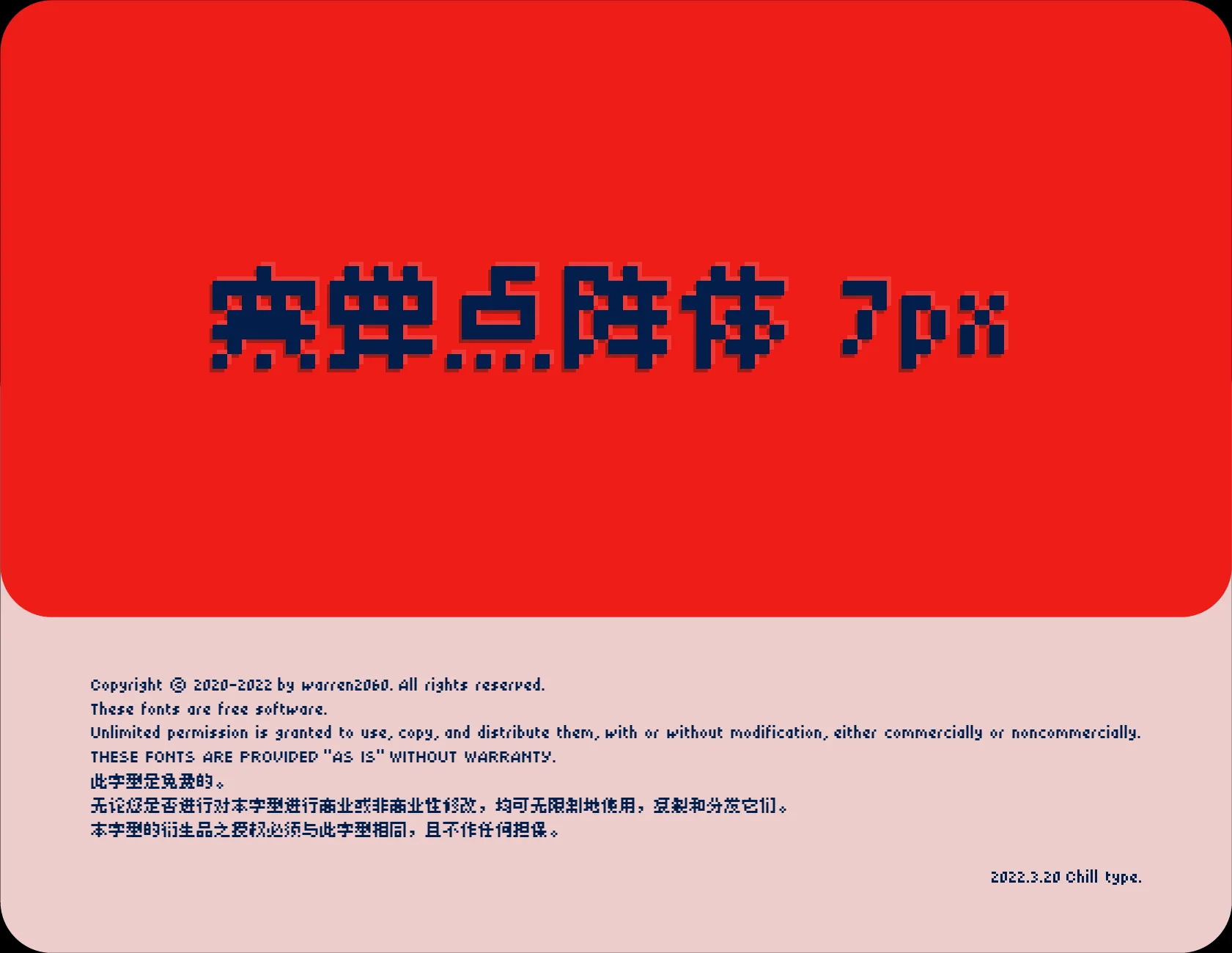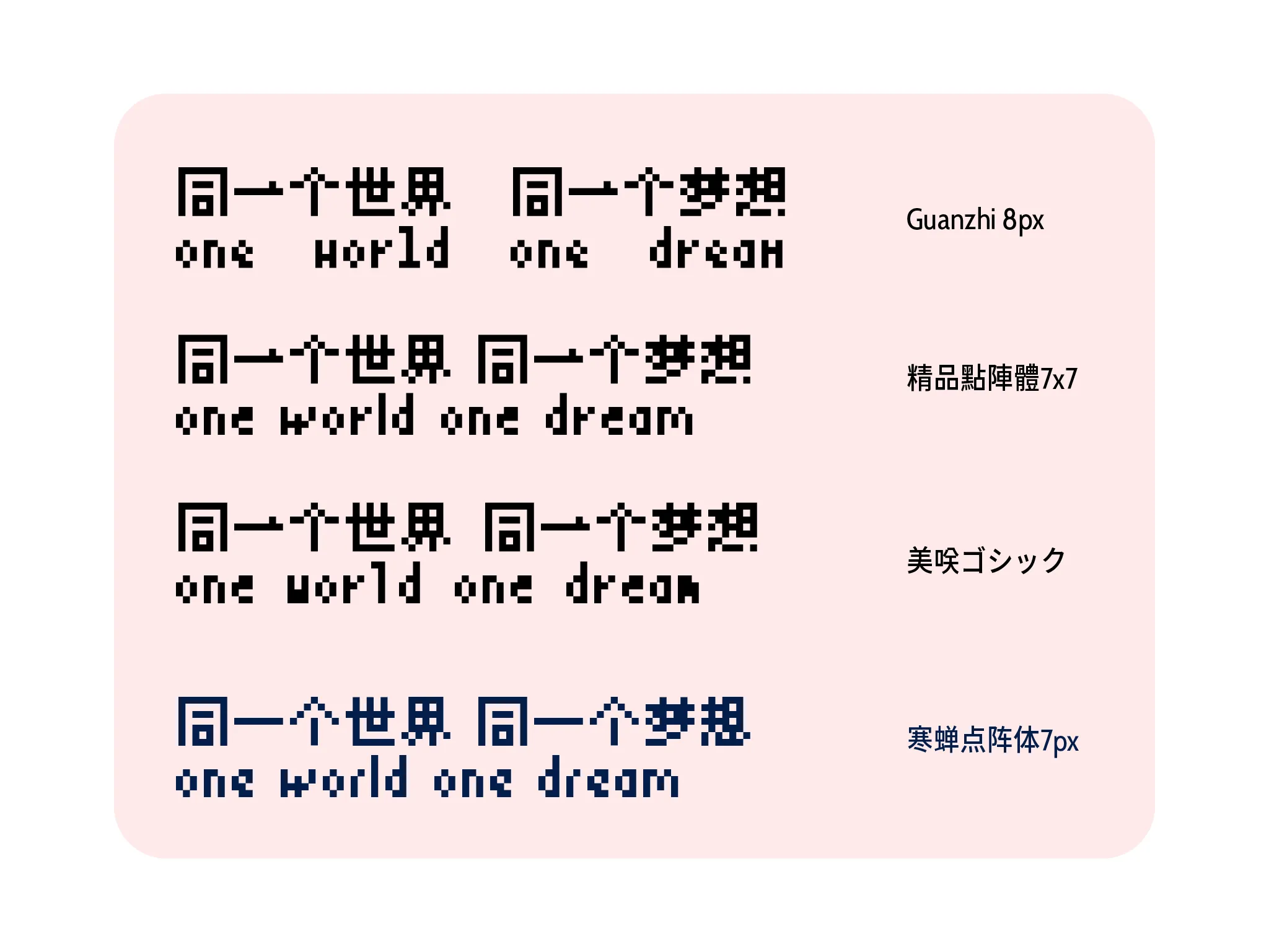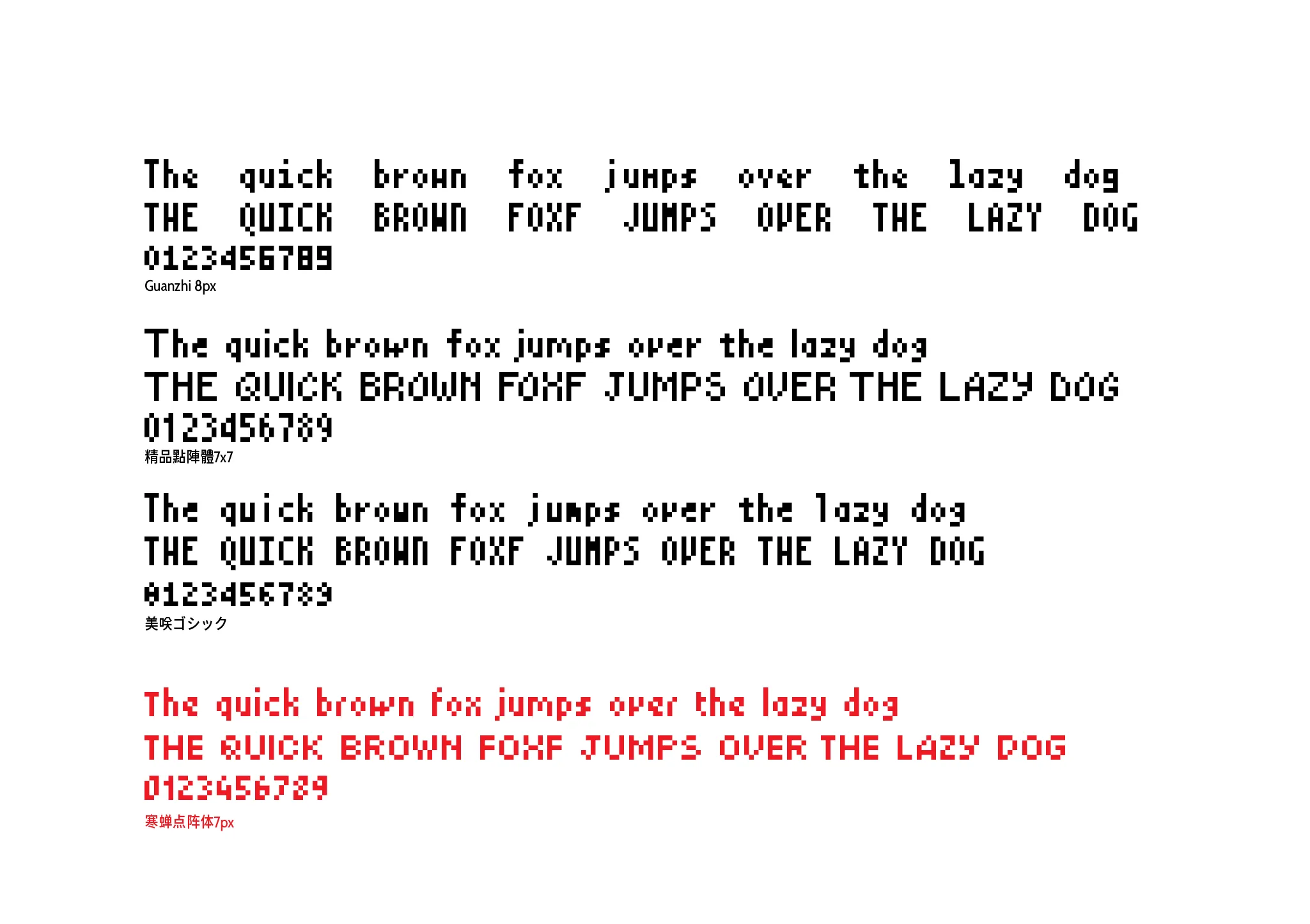
「寒蟬點陣體」是寒蟬字型又一套像素風格的中文字,基於「美咲フォント」修改的字,融合部分「精品點陣體7×7」字形和極少一部分「Guanzhi 8px」的字形。
重新修改設計了英文部分字形和標點符號使其更加協調統,篩選GB2312字符集調整了近2000文字使字形更清晰耐,再設計增加1500多字符,是集日文、繁體、簡體、英文共13600個字符的大成之作,使用更方便。感謝以上開源字型的作者!